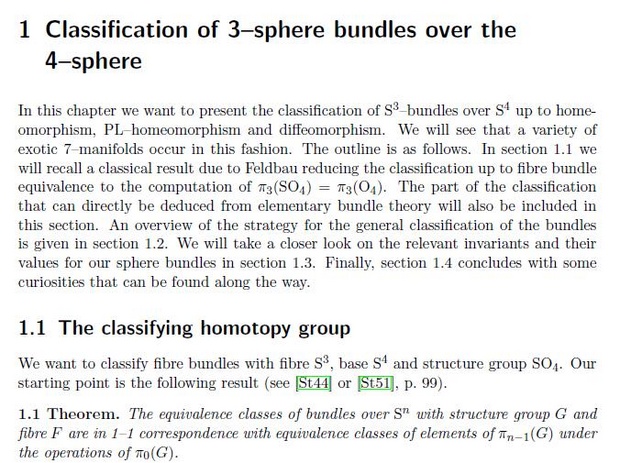
Schrift aus wiss. Arbeit gesucht
ich bin auf der Suche nach den Schriftarten im unteren Bild für meine Abschlussarbeit. Sie stammen aus einer mathematischen Dipl.Arbeit. Ich bin leider kein Mathematiker und kenne mich mit dem Latex Programm mit dem es erstellt wurde nicht aus. What the fond ergab zumindest für die Überschrift Diverda Sans Regular, aber ich bin mir nicht sicher ob das hinkommt. Der Rest blieb leider unerkannt.
Unbestreitbare Stärken der CM/LM sind die vielen verfügbaren Sonder- und Formelzeichen und die vielen verfügbaren Schnitte einschließlich verschiedener Größenzeichnungen. Unter den kostenlosen Schriften gibt es nichts, was auch nur annähernd so umfangreich ist.